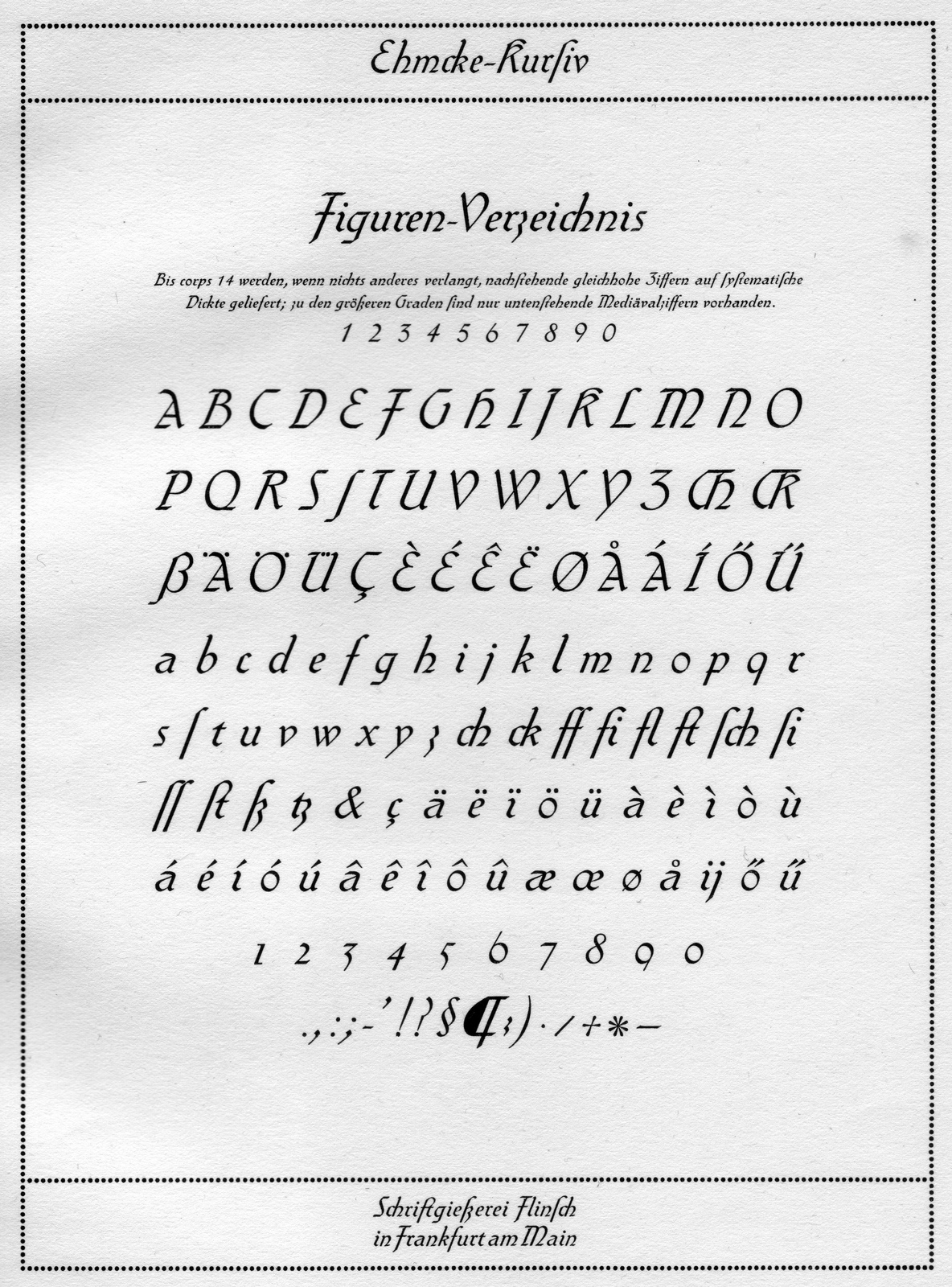
Langes s als Großbuchstabe
Dann laſſt uns doch das runde r ꝛ umdefinieren zu was ähnlichem wie dem langen s! ;-)
Intereſſant finde ich ja hier Wo finde ich denn die Verſalie des ſ zum Behufe des augenſchmauſigen Zitierens? ;-)
Nun, wo es ja eine Versal-Version des ß gibt, indem ja deutlich das ſ drin steckt, wird es wirklich höchste Zeit auch ein Versal-ſ zu erfinden.  Ich fordere mehr Gerechtigkeit für Buchstaben, jeder hat auch eine Versal-Version verdient!  ;-)
Ein großes ſ gibt es einigen lateinischen Schriftsystemen für Sprachen im Kakasus.
Und laut Quelle ist sogar die Aufnahme ins Unicode vorgeschlagen, aber ...
... wie gewonnen, so zerronnen: Das große ſ entfleucht samt dem kleinen ſ aus dem mitteleuropäischen Unicode, weil ein spezielles kaukasisches kleines/großes ſ vorgeschlagen wird, da das kaukasische nie eine Serife links hat und damit es wegen dem großen ſ kein Kuddelmuddel mit dem mitteleuropäischen ſ gibt ...
Und laut Quelle
Wer sich nicht durch ein 52-seitiges PDF wühlen will: das kaukasische große ſ steht auf Seite 12 und sieht etwa aus wie das IPA-Zeichen ʕ.